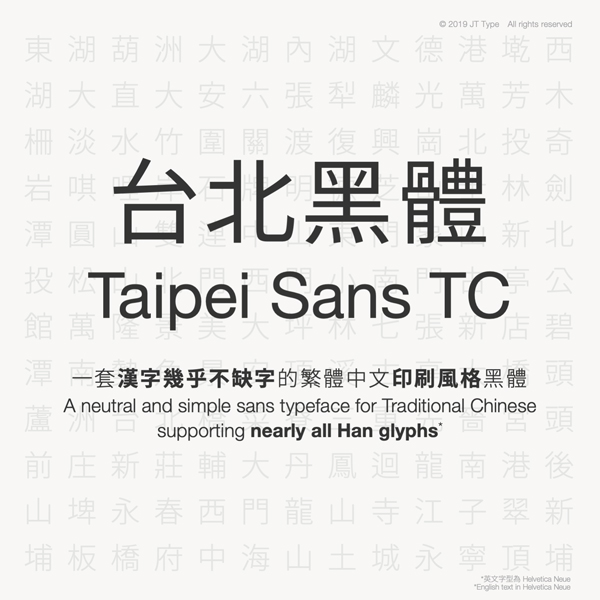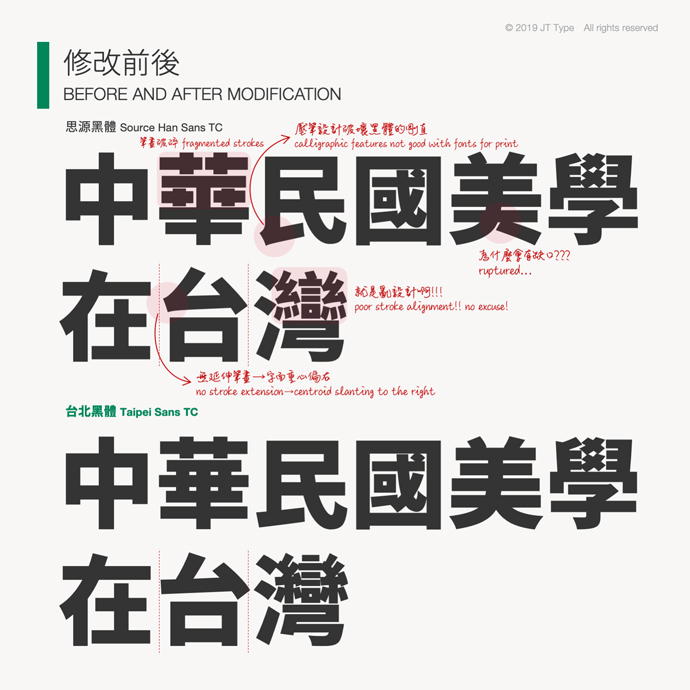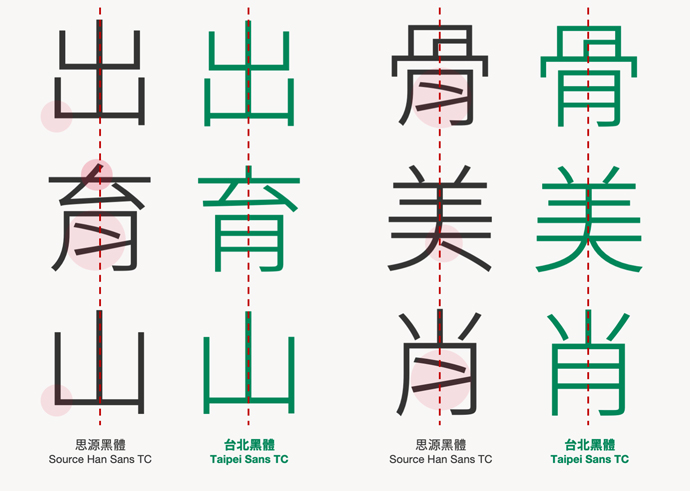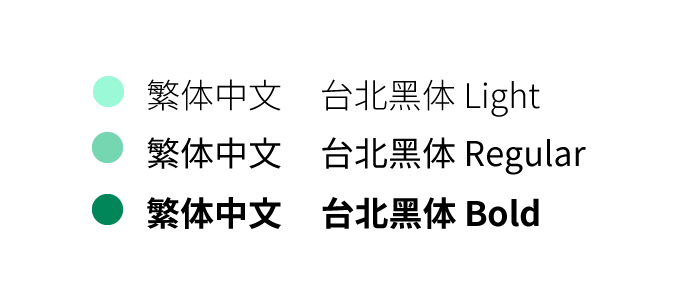
一套适合印刷的繁体中文字体可免费商用字体资讯
近日又一款免费可商用的中文字体上线公测,台湾黑体。
创作背景
商免黑体很多,像思源黑体、阿里普惠黑等,但是适合用于印刷的免费黑体非常少,因此,  翰字铸造以开源的思源黑体(Source Han Sans)为基础进行改作,设计出了一款繁体中文字体-台北黑体。
字体字重
这款字体目前共有三个字重,light、regular、bold,后续几年会逐渐补充其他4个字重extralight、normal、medium、heavy,以满足各类设计之进阶需求。
字体的特点
相比思源黑体,台北黑体调整了字体结构的平衡感,字体更加对称。
字体的使用范围
2、 「汉字几乎不缺字」, 台北黑体的改作基于思源黑体的 KR 版。汉字都已尽量统一为印刷风格并符合当代习惯。